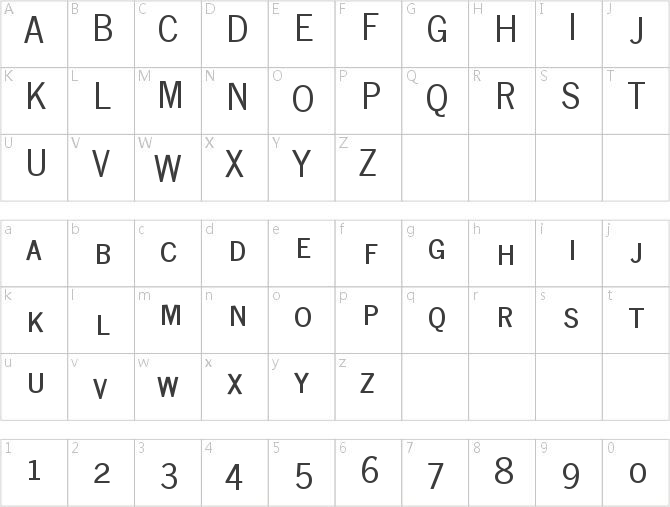
NewsGothicSmc 詳情頁(yè)
NewsGothicSmc字體字庫(kù)是一款讓人賞心悅目、百看不厭的英文字體,適合各類(lèi)廣告和產(chǎn)品包裝設(shè)計(jì)應(yīng)用,字體大小0.05MB,格式為ttf字體,上傳用戶(hù)是我,Dirac,作者/版權(quán)方為未知